Un de mes petits marronniers préférés : la typographie, et ça fait quelques mois que je n’en avais pas reposté sur le blog. Découvrez et téléchargez ces 16 polices d’écritures de qualité. A utiliser sans modération dans vos compositions l’année prochaine.
Tandis que cette année touche bientôt à sa fin, j’ai profité de l’accalmie pour trier les ressources mises de côté au cours des mois passés. Et les typographies sont légions. Vous vous en doutez, je ne télécharge pas chaque typographie sur laquelle je tombe, ni même à chaque fois qu’une me plaît, ou je ne m’en sortirais pas. Mais à force de mettre celles-ci en favoris, ça commence à faire. J’ai donc décidé d’en retenir quelques-unes, et de vous les proposer par la même occasion en guise de bookmark. Et puisqu’il faut se donner les moyens de ses ambitions, il y a de tout : certaines sont gratuites, mais d’autres sont payantes.
- Albert est l’œuvre de William Bayley Suckling, un étudiant en design de 22 ans du London College of Communication. Avec un côté kitsch résolument assumé, Albert est une police de titre décorative inspiré par la signalétique victorienne.
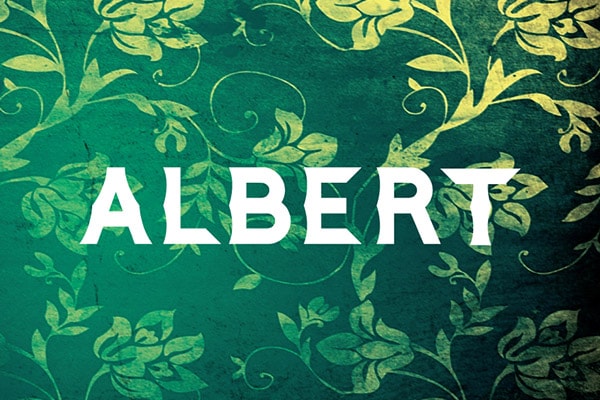
- RBNo2 est inspirée des polices industrielles du XIXème siècle. Combinée avec des styles de typo plus classiques, cela en fait une partenaire idéale pour les visuels techniques et contemporains.
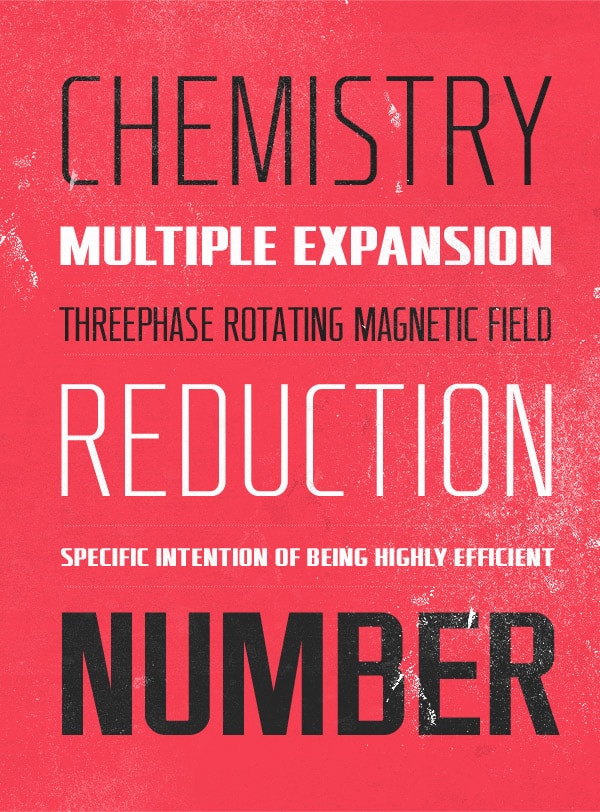
- Bellaboo, cette typographie toute en capitales de Marcelo Reis Melo contient les caractères latins, mais aussi suédois. De quoi ajouter un petit je ne sais quoi à la saveur excentrique à vos compositions.
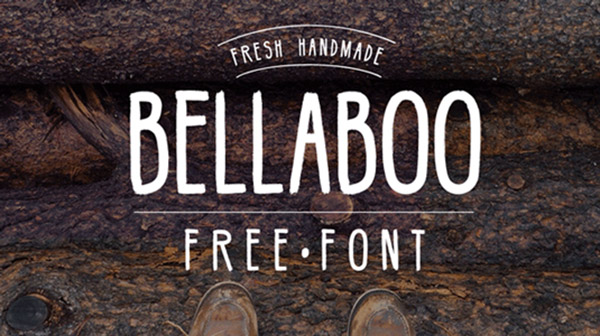
- Conçue par le designer Hanson Chan, Walk On est une police rétro avec une approche contemporaine. Initialement conçue comme une police d’entreprise pour la marque Wang & Lynch, elle est maintenant disponible au public. Avec des formes simples et des structures ornementales, elle sera parfaite pour les gros titres.
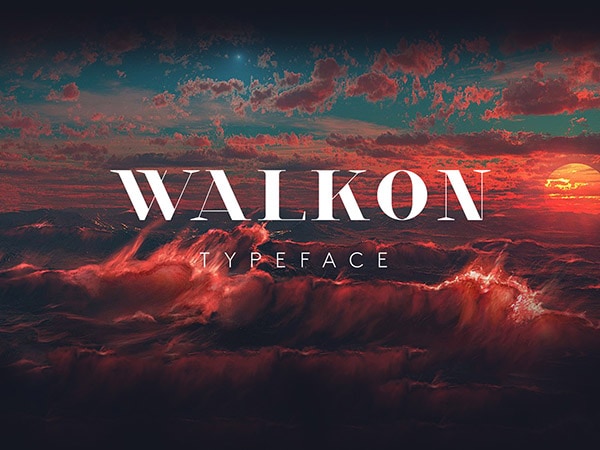
- Matt Ellis, graphiste et étudiant canadien est l’auteur d’Ikaros, un sans-sérif moderne. Avec un chouette travail sur les hauteurs des majuscules et des minuscules, ainsi que sur les chiffres et des symboles, Ikaros donnera du punch à vos créations.
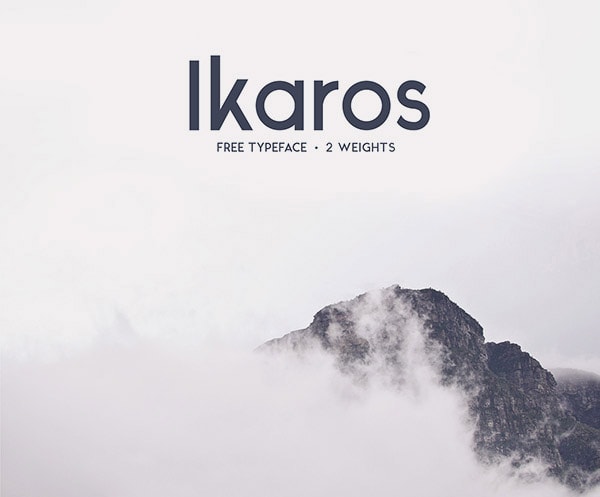
- Nougatine a été créée par un graphiste français, Fabien Laborie. Ce dernier décrit cette fonte comme « une fonte de titrage inspirée par la saveur des cookies sortants du four ». Livrée avec 380 glyphes, une grande quantité de variantes et un ensemble de lettres alternatives, cette typo se prêtera très bien au titrage.
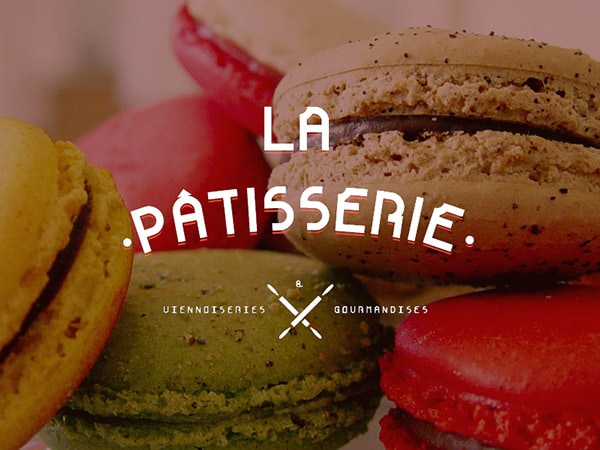
- Salamander Script est une police d’écriture particulièrement fluide. Comme avec toutes les polices de Fenotype, Salamander Script est livrée avec un véritable déluge d’options OpenType. Une police aussi divertissante que vivante à ajouter à votre collection.
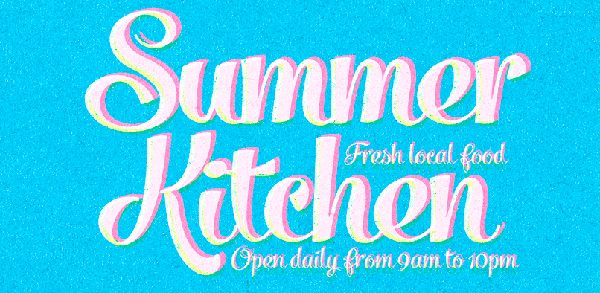
- Vagtur est à l’origine un projet universitaire issu de la collaboration entre deux graphistes, Simon Becker et Sabrina Ekecik. Il s’agit d’une police de titre qui dispose d’un fort contraste entre des arrondis sans-sérifs et l’écriture calligraphique. Ceci n’est pas un hasard, puisqu’elle est la rencontre des fontes VAG et Fette Fraktur.
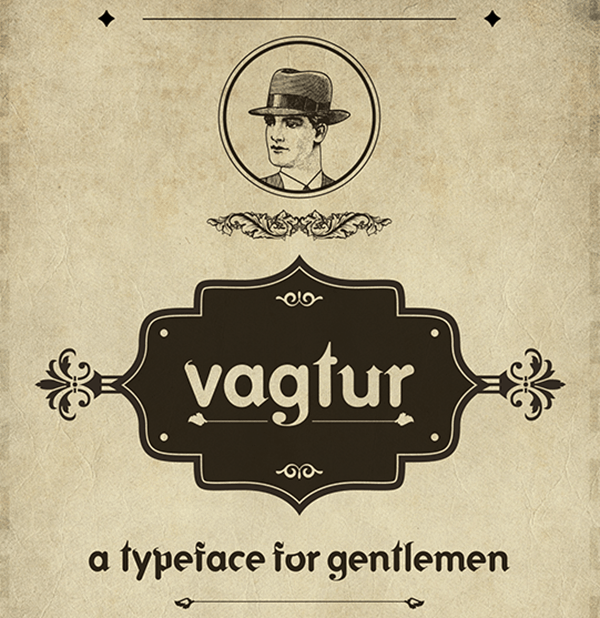
- Rocket Script pourrait tout à fait trôner sur l’enseigne d’un fast-food US du Nevada. Cette police rétro rappelle incontestablement les années 50 et elle aurait toute sa place dans ma sélection de typo à hipsters.
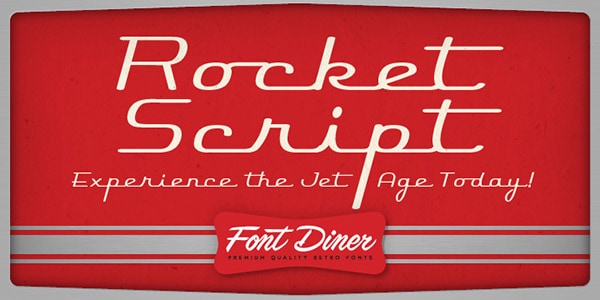
- Abraham Lincoln est une police absolument magnifique, créé par la designer Frances MacLeod. Originaire de Wichita, au Kansas, Frances a créé cette typo pour résoudre le problème d’une recherche constante d’une sérif condensée.
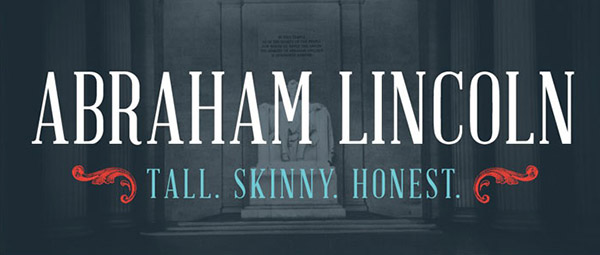
- Du lettrage ombragé aux doubles lettres ligaturées, Microbrew est une police prototype. Au-delà d’une application limitée au titrage, elle a l’avantage de contenir un ensemble de symboles et d’ornements en bonus.
- Voici Metronic Slab, une police mécane bien équilibrée. Les empattements bien définis assurent à cette typographie une forme cohérente. Elle comprend également un ensemble d’icônes utiles pour la conception d’interfaces.
- Avec plus de 600 glyphes, Gist est une typo vraiment très riche. Et si vous n’êtes pas convaincu de la majesté de Gist, vous pouvez vous contenter de la Gist light.
- Comic Neue à fait parler d’elle voilà quelque temps maintenant, puisqu’il s’agit d’une remasterisation de la très détestée Comic Sans MS. Avec un dessin bien redéfini, cette création de l’australien Craig Rozynski peut parfois être une solution de repli intéressante. De repli, car bien qu’elle soit équilibrée et réussie elle garde toutefois la trace de sa mésestimée grande sœur.
- Reckoner a été créée par Sydney Alex Dale. Son auteur la décrit comme industrielle avec une touche moderne, tout en conservant les principes fondamentaux d’une police traditionnelle.
- Ailerons est quant à elle inspirée par les modèles d’avions des années 40. Propre et toute en capitales, elle a été conçue à l’origine pour un projet expérimental de modèles d’avion. Depuis, le designer brésilien Adilson Gonzales de Oliveira en a fait cette typographie à usage personnel.